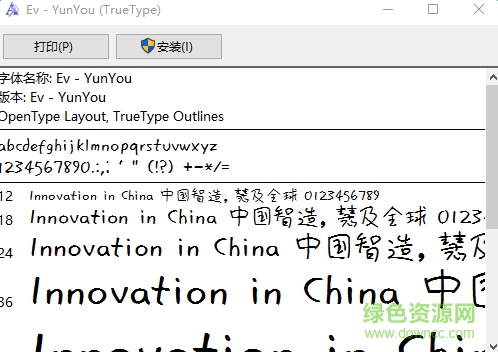
云游體是一款很好看也很實(shí)用的電腦字體,正是因?yàn)檫@款字體有著它獨(dú)特的魅力,所以很多年輕人都喜歡用這款字體,如果大家也喜歡的話可以隨時(shí)來(lái)綠色資源網(wǎng)下載。
云游體這款字體是真的很不錯(cuò),寫出來(lái)的字效果很不錯(cuò),不管是用于書(shū)畫題詞題字,還是廣告設(shè)計(jì)都是可以的,歡迎大家來(lái)綠色資源網(wǎng)下載。